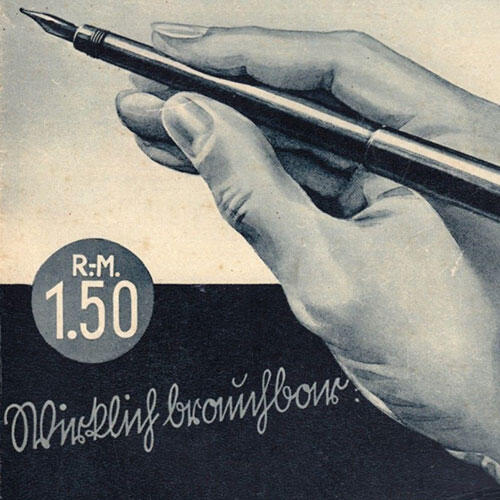
- 1915
- Gebrochene Schrift
Die Deutsche Kraft ist eine kräftige Kurrent-Schreibschrift des Schriftgestalters Albert Christoph Auspurg. Die Schrift erschien 1915 in einem Schnitt bei Ludwig & Mayer. 1928 wurde von der gleichen Gießerei noch ein leichter Schnitt veröffentlicht. Eine Digitalisierung beider Schnitte gibt es bei Delbanco-Frakturschriften.
Originalmuster von Ludwig & Mayer
Digitalisierung von Delbanco-Frakturschriften